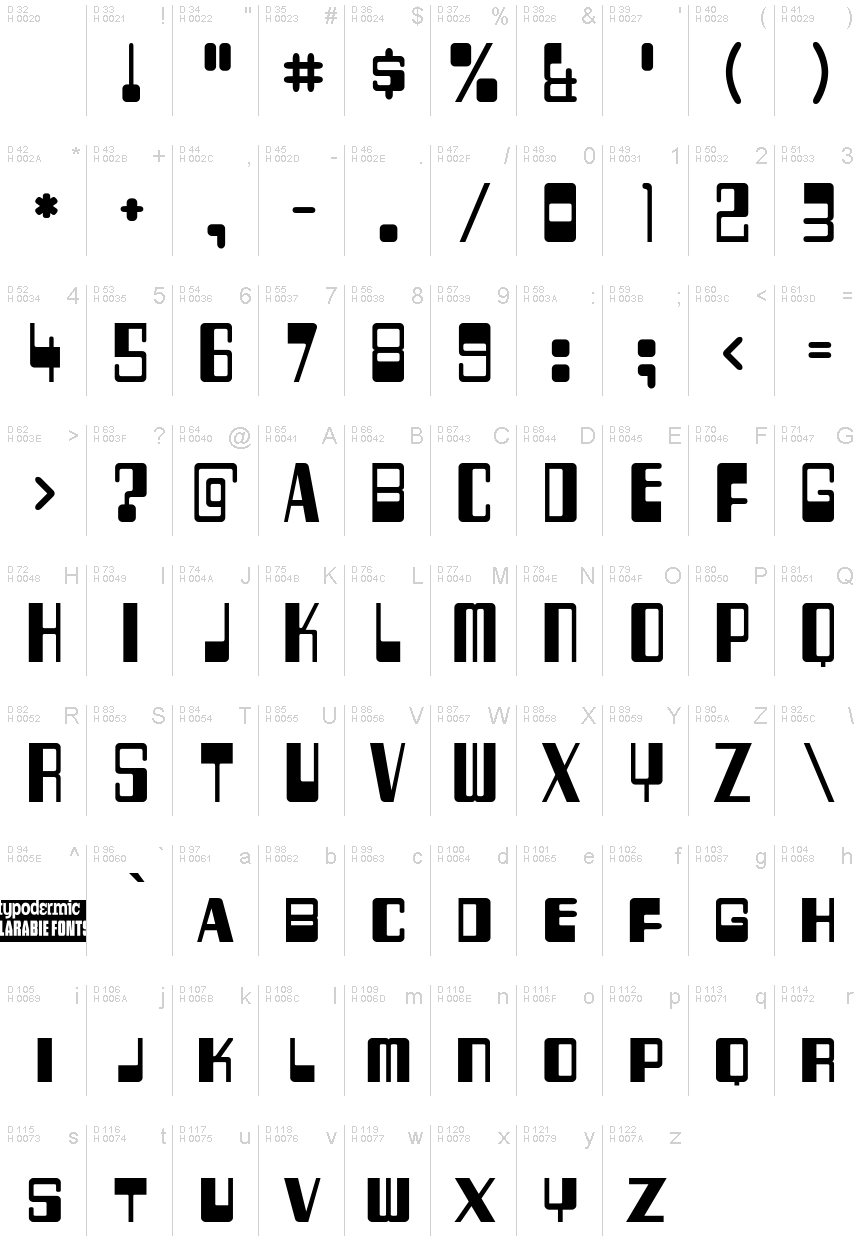
"256 Bytes" es una tipografía display impactante diseñada por Ray Larabie. Su estética futurista y condensada evoca una sofisticación tecnológica y elegante. Sus formas angulares y nítidas, junto con sus trazos geométricos, logran un aspecto audaz y actual. Gracias a su ancho compacto, es perfecta para titulares llamativos, interfaces digitales y proyectos de branding que busquen una identidad visual moderna y contundente.
El estilo minimalista y monocromático de "256 Bytes" encaja en una gran variedad de contextos, desde tecnología de vanguardia hasta el diseño innovador de envases.